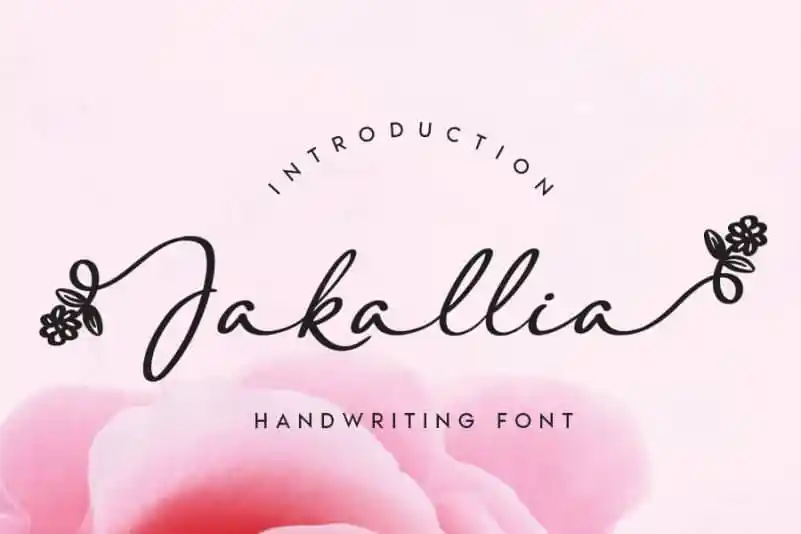
Jakallia Handwritten Font – Download Grátis
Jakallia Handwritten Font é uma hermosa fonte escrita a mão que traz uma pitada de criatividade à sua próxima obra. Seu design única inclui caracteres temáticos florais e extras, adicionando um toque adorável para suas criações em projeto casinha e outras iniciativas DIY. Independentemente se você está buscando fontes para Instagram ou scripts de caligrafia para projetos DIY autogerenciados, Jakallia irá transformar qualquer idéia criativa numa verdadeira obra de arte.